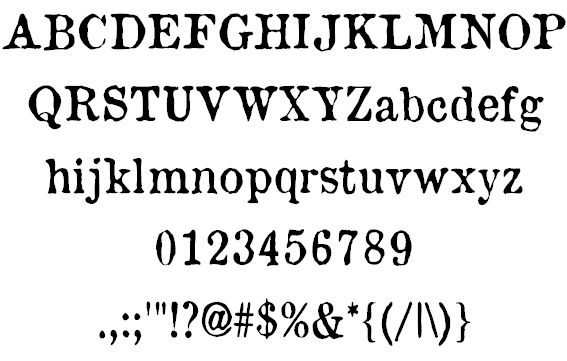
7. Ст Нижегордоский
Ст Нижегордоский — кириллический шрифт с ярко выраженным художественным оформлением. Его уникальные формы символов и стилистические особенности делают его идеальным для проектов, требующих творческого, нетрадиционного подхода, таких как плакаты, логотипы или упаковка.
8. Ninova
Ninova — современный и элегантный шрифт, который отлично подходит для создания дизайнов, требующих утонченного и изысканного вида. Его четкие и простые линии облегчают чтение, а уникальный стиль и декоративные элементы добавляют изюминку.